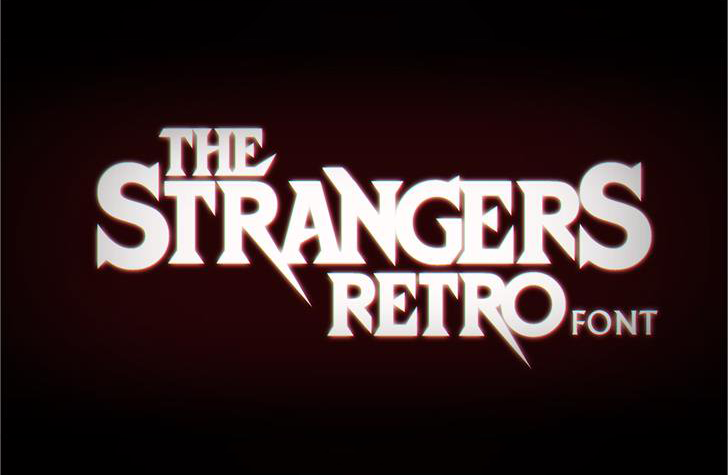
Strangers Retro Font – Download Grátis
A fonte ‘Strangers Retro Font’ foi projetada para rememorar a década de 80 e 90, um período marcado pela estética retro e nostalgia. Essa fonte inspira design vintage com sua simplicidade elegante e detalhes sutis que se adequam perfeitamente a labels, badges e posters clássicos. Este tipo digital oferece uma paleta variada de letras maiúsculas e minúsculas, assim como números e símbolos adicionais. Ideal para reviver o espírito dos anos 80 e 90 em suas criações, seja em t-shirts, rótulos de embalagens ou qualquer outro estilo vintage. Com seu design cuidadosamente projetado, ‘Strangers Retro Font’ é perfeito para aqueles que querem adicionar um toque nostálgico a seus designs modernos. Esta fonte não só mantém o respeito pela história e estética do passado, mas também oferece a liberdade de expressar suas ideias de maneira contemporânea e criativa. Seja para criar uma identidade visual que remete à década passada ou para adicionar um toque vintage a sua próxima camiseta de grife, esta fonte trará personalidade e estilo aos seus projetos.